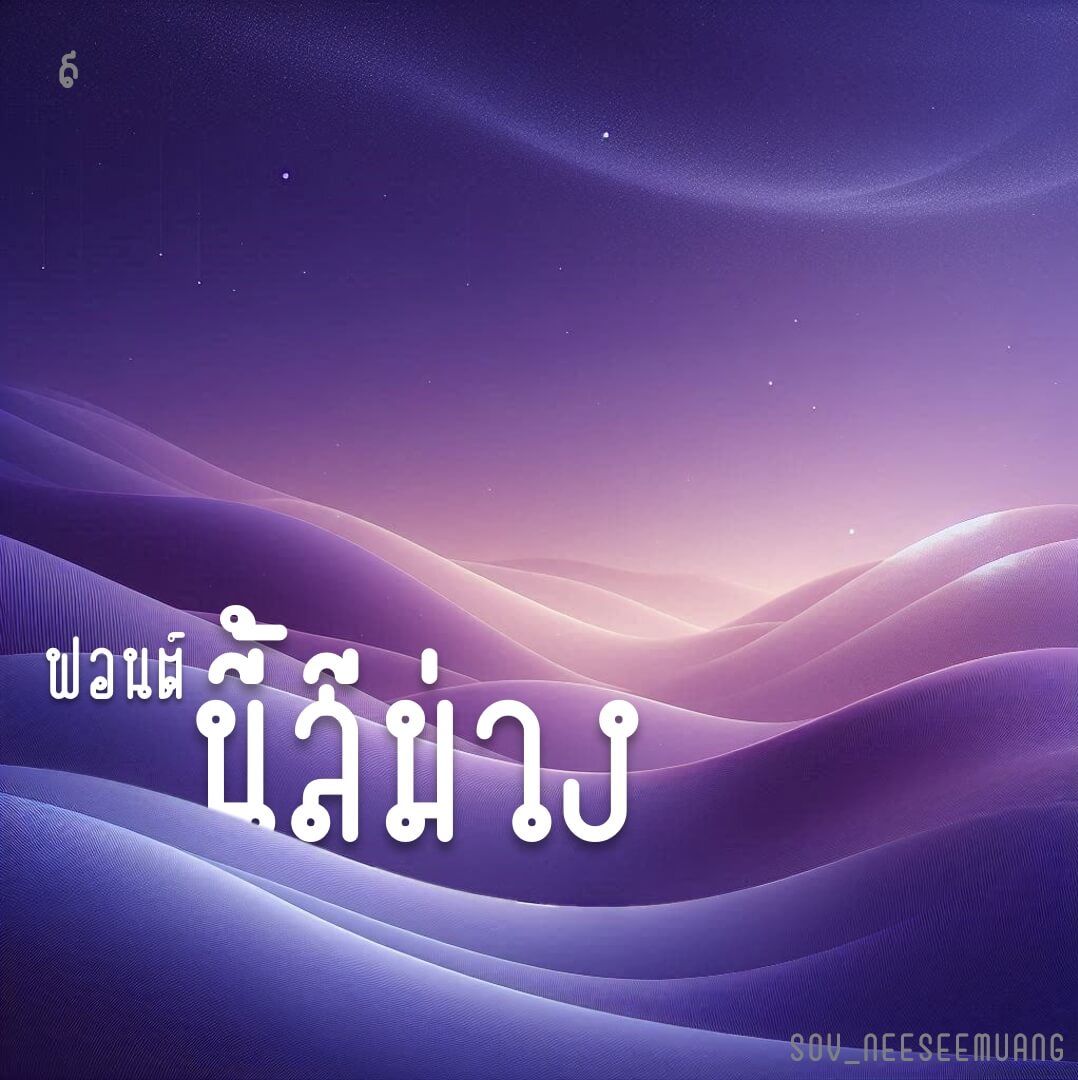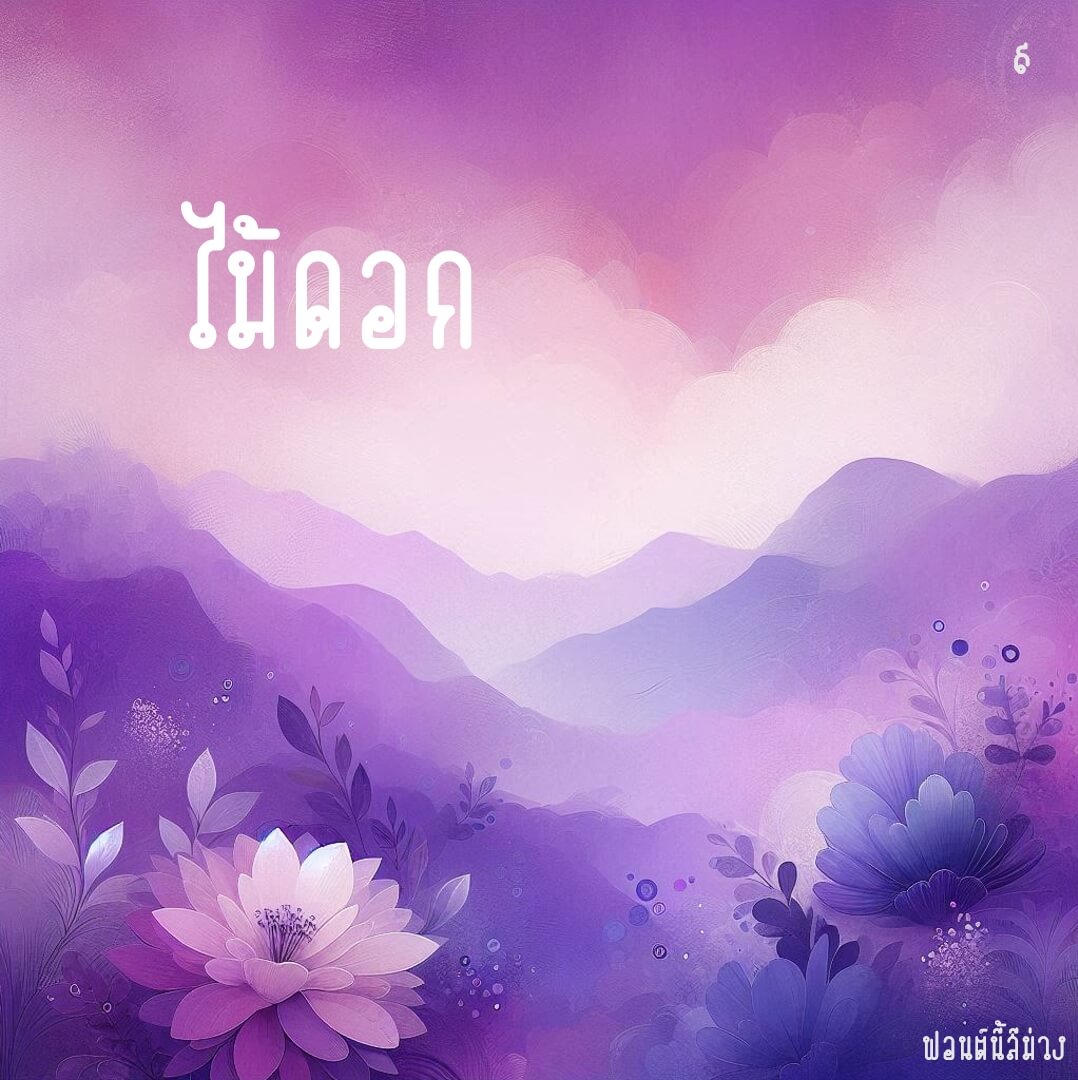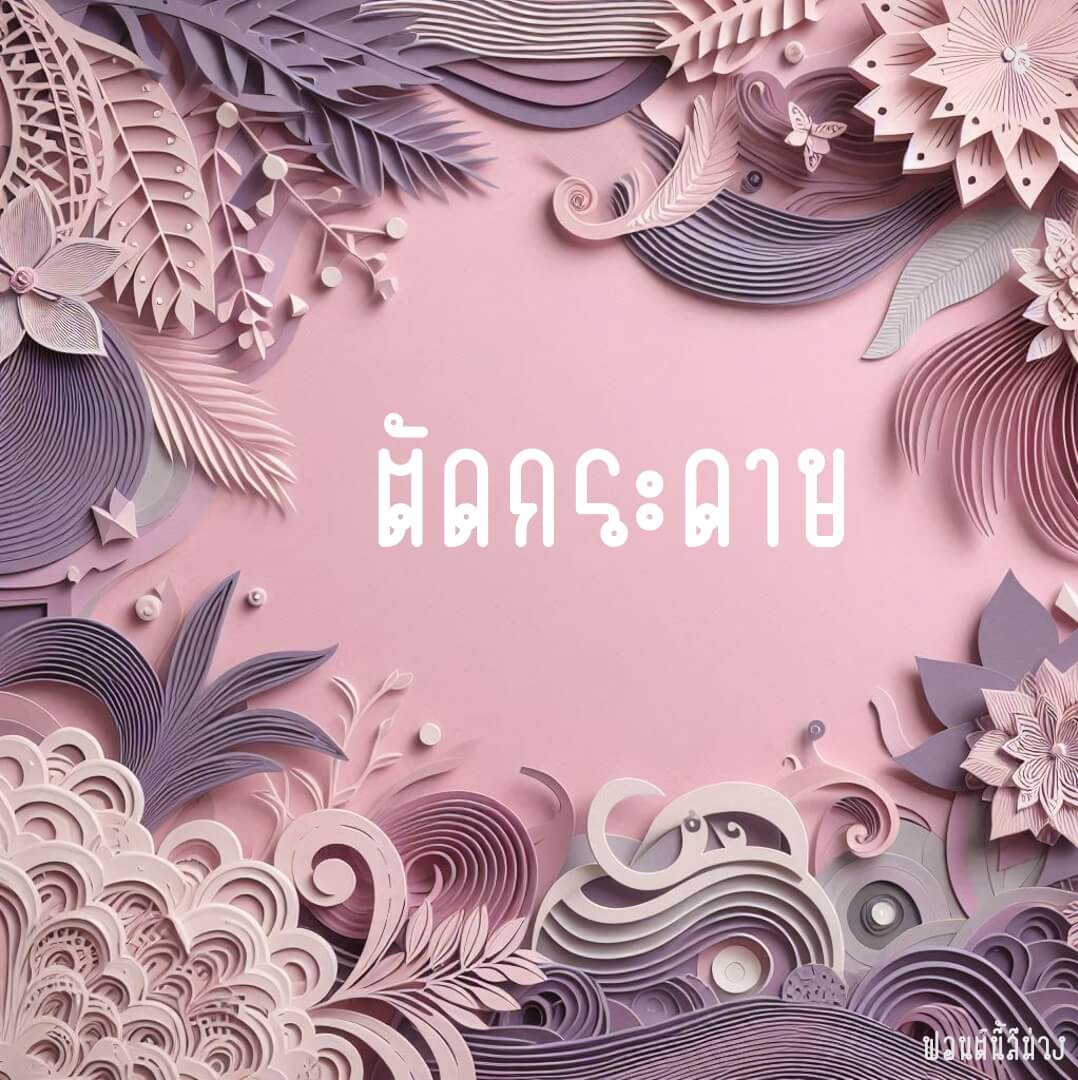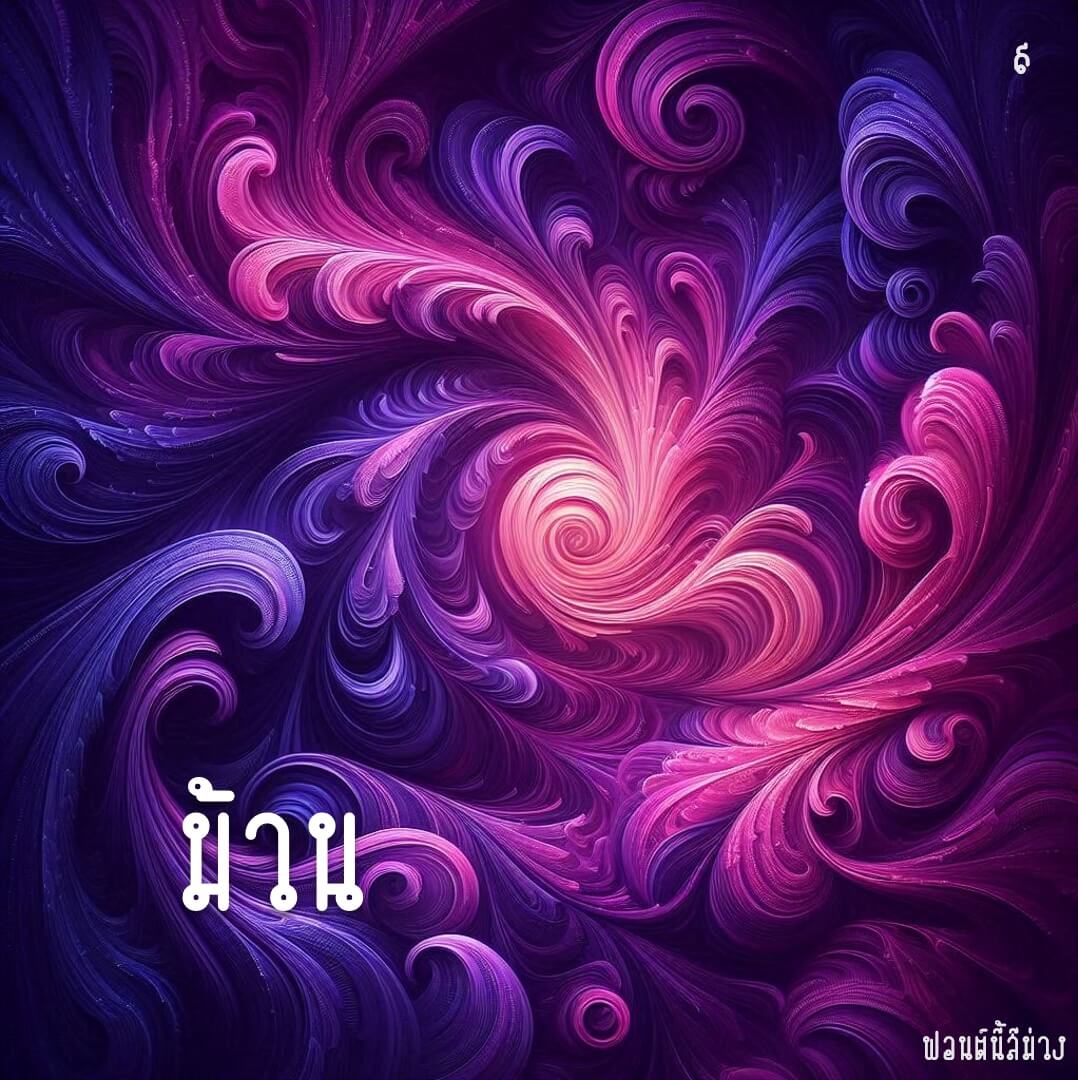
ฟอนต์นี้สีม่วง ตอนแรกมันออกแนวฟอนต์หัวถั่วงอก พอดีเพื่อนบอกอยากได้ฟอนต์สีม่วง… เลยขยับหัวให้อยู่ตรงกลางให้สร้างความสับสนนิดนึง
เบื้องหลังการออกแบบ : ฟอนต์ นี้สีม่วง
นี้สีม่วง (SOV_NeeSeeMuang)